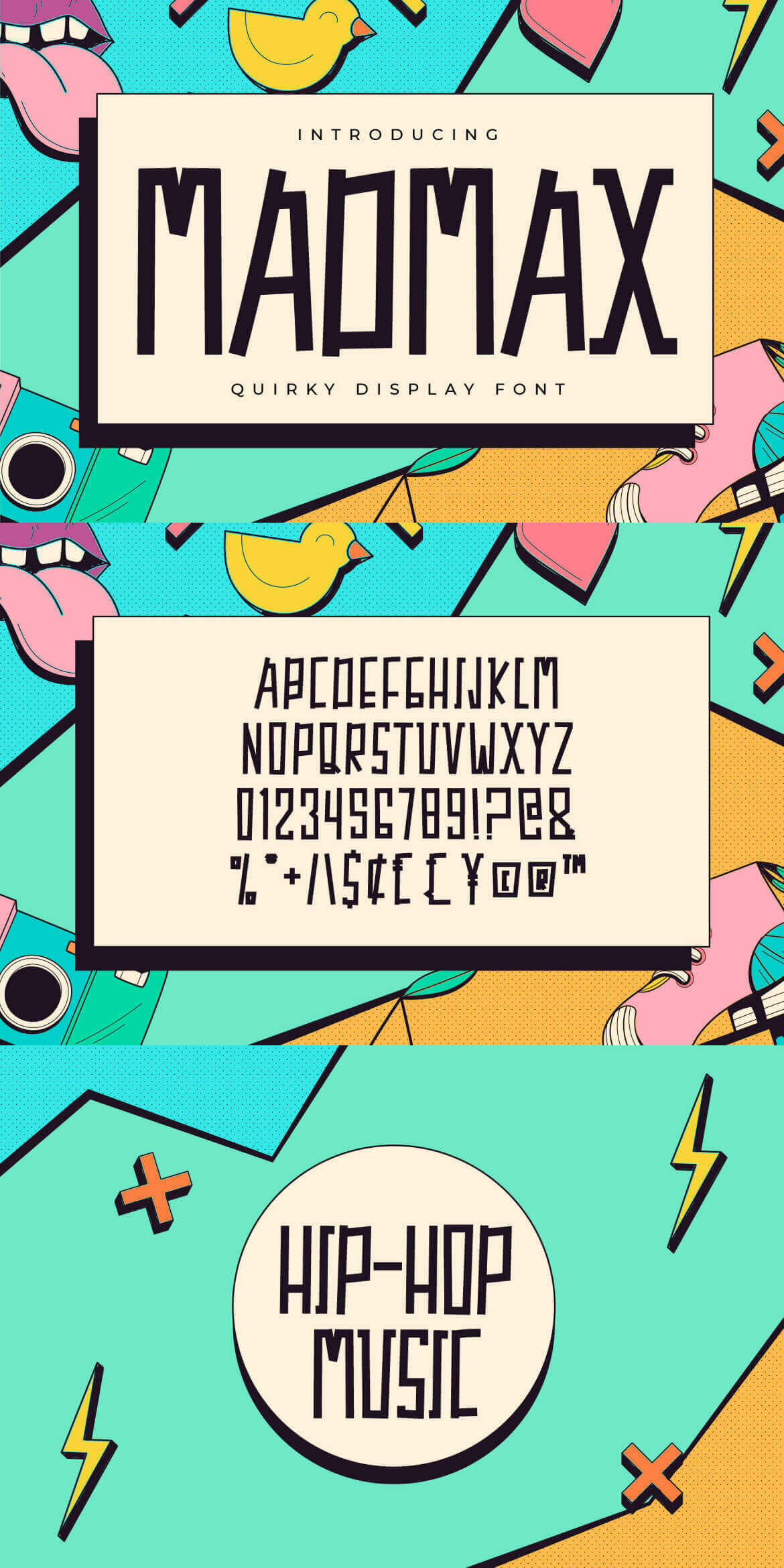
Шрифт - Madmax
Madmax - необычный и симпатичный шрифт, который подходит для самых разнообразных проектов Его непринужденный шарм делает его очень легким для чтения и универсальным. Добавьте этот красивый дисплейный шрифт к лучшей своей творческой идее.